管軍千戸所印>年記部分拡大
年記部分拡大(左側:大徳二年四月日、右側:「中書省」か?)
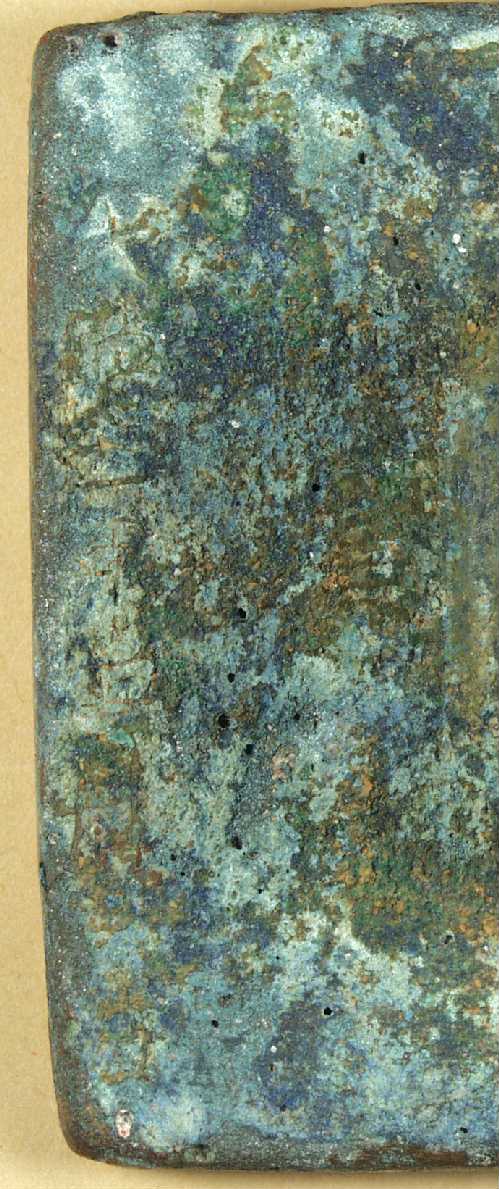
吉池孝一「管軍千戸所印(パスパ字漢語)一顆」(『KOTONOHA』第18号、2004)はこの印の
背面に年記があることを指摘し、腐食によってかなり見づらい状況にあるものの、
その文字を「大徳[不明]年四月」と読み、「年数部分は不明瞭。「二」もしくは「三」の
ようにも読み取れる」とした。すなわち、「大徳二年四月」ないし「大徳三年四月」と読んだ
訳である。今回さらに詳しく調べた結果、新たにいくつかの点が確認できた。
(1)年記部分は「大徳二年四月日」と見えること。
(2)年記部分の右隣(鈕の左)に正確には読み取れないが最低三文字が刻まれていること。
(3)その三文字が「中書省」である可能性があること。
まず、(1)について。肉眼で背面を直視した場合には、当該箇所の数字は判然としない。横の
線が2本はっきりと確認できるが、その上下にも何らかの線があり、「二」か「三」かの判断
は容易ではない。しかしパソコン上で画像を拡大し、さらに多少のデジタル処理を施して眺める
と、「二」の上部に見えた線は「徳」の右下の「心」の部分であり、「二」の下部に見えた線は
「年」の第2画の線であることが確認できる。「徳」の「心」の部分は第2画の線が比較的短く、
この時代の貨幣「大徳通宝」の「徳」の字形によく似ている。
さらに、年記の末尾に「日」の字が確認された。「月」字の下にたっぷり1字分の余白があり、
最下部に「日」字が見える。このように「月」と「日」の間に数字を入れずに余白を設ける方法
は他の官印の背記にもよく見られるものであり、また碑文の年記にも確認される形式である。
結局、本印は大徳二年(1298年)四月のものと断定してよい。私印では通常このような背記が
ないため、正確な製造年を知ることができないが、官印の場合それを特定することができ、文
字研究の面からは大いなる恩恵となりうる。
次に(2)および(3)について。厳密に言えば、この部分には確実に同定しうる文字は存在しない。
官印全般の体例に照らして、この部分にはこの印を製造した役所名が記されているはずであり、
そのような予見に基づけば、「中書省」のように読めなくもないということにすぎない。
他のパスパ文字官印ではこの部分に「中書礼部造」「行中書省造」などとあり、本印でもその
ような記載が期待される。画像では鈕のすぐ左側の中央に数本の横線(これを今仮にBとする)
が確認でき、さらに下部に「省」ないし「造」と見なしうるような影(これをCとする)が見
える。Bはその横線の数から推して「書」「車」「庫」などのような文字と思われるが、Cを
「造」と想定した場合、文字Bが役所名の末尾ということになり、「書」「車」「庫」などでは
多少の不自然さを免れない。もしCを「省」と見なせば、Bは「書」である可能性が高く、
はっきりとは見えないがその上の部分(A)に「中」を想定できる。その場合、他の印に見ら
れる「造」の文字が本印では欠けていることになるが、単に確認できないだけで実際にはいずれ
かの箇所(例えば次の行の中央)に記されている可能性も考えられる。
また、他の印の例から
すれば、「中書省」という大官庁名のみというのは不自然であり、具体的に「中書礼部」または
地方官庁たる「行中書省」とあることが多いから、本印の場合にも最上部に「行」が刻まれて
いた可能性があるが、残念ながら全く確認できない。
いずれにせよ、この部分はすこぶる不明瞭 であり、「中書省」も一つの可能性としてのみ提出しておく。
なお、他の官印では鈕の右側に印面のパスパ文字と同内容の漢字が刻まれているから、本印 でも「管軍千戸所印」という文字があるはずであるが、腐食が激しくほとんど確認できない。